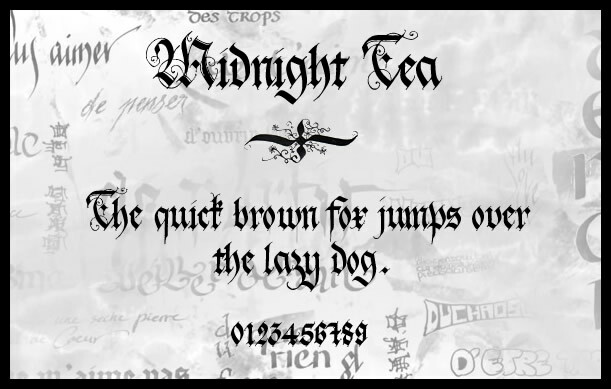
Holyrose-midnightea von Typeface ist eine kostenlose mittelalterliche Gothic-Schrift. Schwere, tintengetränkte Striche und dolchartige Kurven verleihen jedem Wort die Anmutung von Steinmetzarbeiten an einer Kathedrale oder den Aufzeichnungen in einem alten Grimoire. Die Buchstaben stehen eng beieinander, mit scharfen Dornen und dichten schwarzen Formen, die das Auge in eine düstere, atmosphärische Textur ziehen.
Mit Holyrose-midnightea heben Sie Logos von Metal-Bands, düstere Fantasy-Buchcover, Horror-Poster, Spieletitel, okkulte Zines und Gothic-Event-Flyer auf ein dramatisches neues Level. Diese kostenlose Schrift glänzt besonders in großen Größen, wo ihre gezackten Details gestochen scharf bleiben. Kombinieren Sie sie für Begleittexte mit einer klaren, geometrischen serifenlosen Schrift, um die Lesbarkeit Ihrer Layouts zu wahren, ohne die düstere Stimmung zu verlieren.